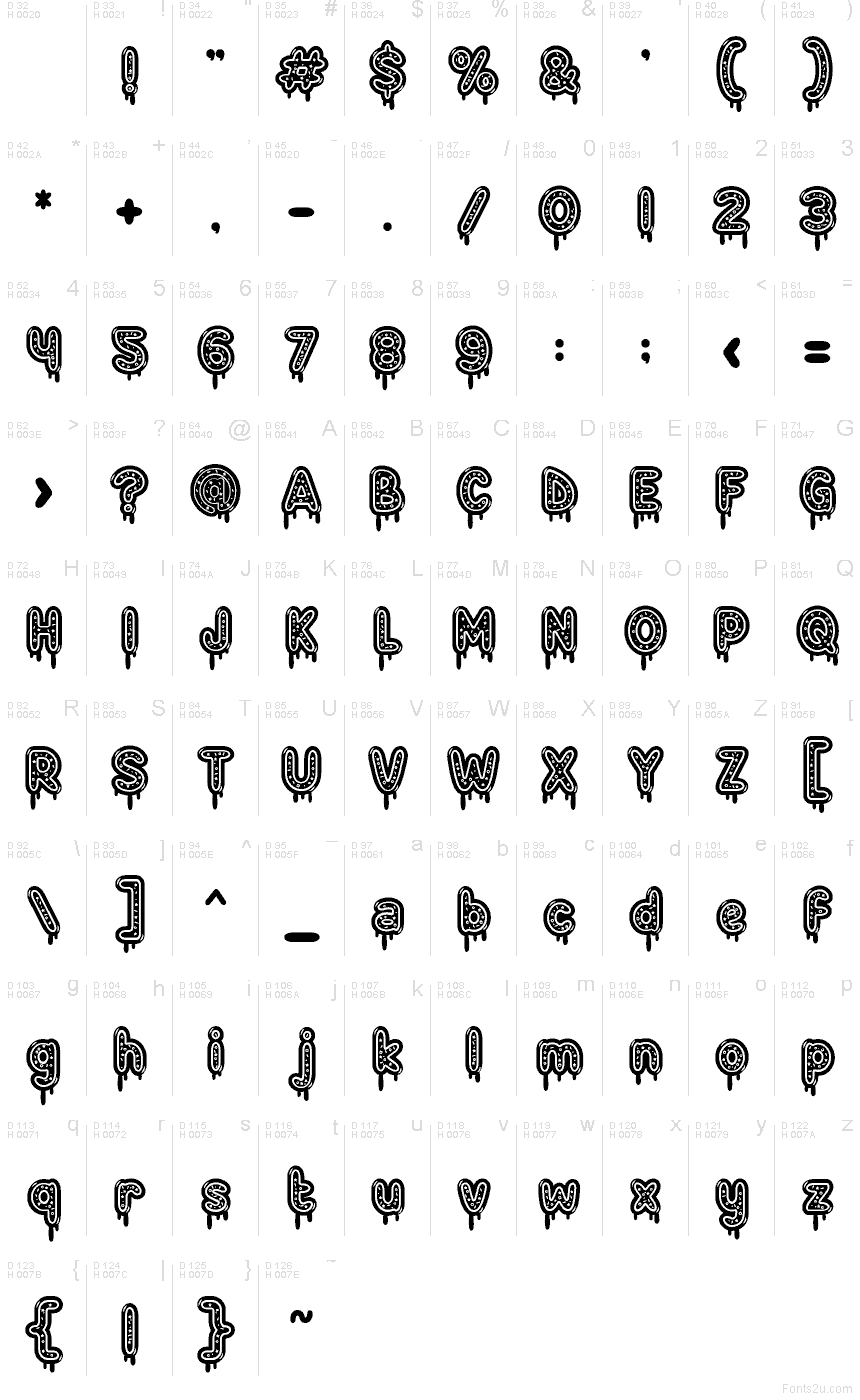
Cake Couture Six
Cake Couture Familie zusammengesetzt aus 10 Schriftarten
Cake Couture Six von Putracetol Studio ist eine kostenlose Display-Schrift, die wie frisch mit Zuckerguss verziert aussieht und sanft verläuft. Die Buchstaben wirken rund, voluminös und verspielt – perfekt für einen Candy-Shop. Mit den eingearbeiteten Sternen und Punkten wirkt das gesamte Alphabet eher wie eine liebevoll dekorierte Geburtstagstorte als eine reine Displayschrift.
Diese zuckersüße Stimmung macht es zu einem idealen Font für Bäckerei-Branding, Einladungen, Verpackungen für Kinder, Speisekarten in Cafés oder Postertitel, die einen verspielten, handgemachten Look brauchen. Auch für Cover-Designs, Social-Media-Grafiken und kurze Schriftzüge eignet sich die Schrift hervorragend, da die tropfenden Enden und die Streusel-Details den Großteil der Gestaltung bereits übernehmen.